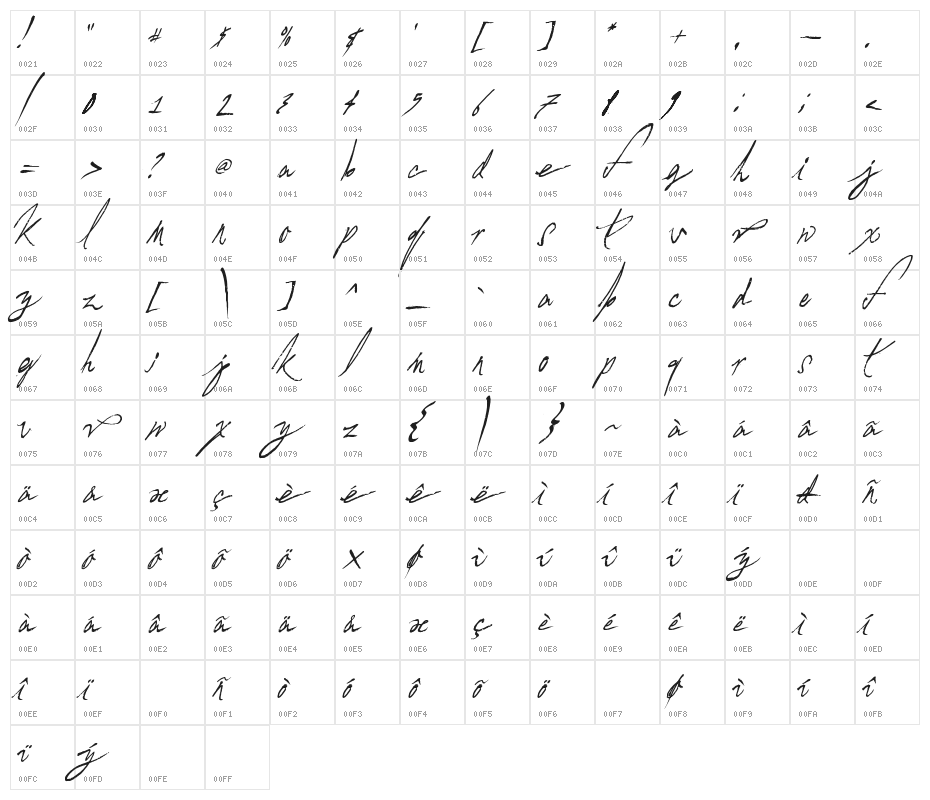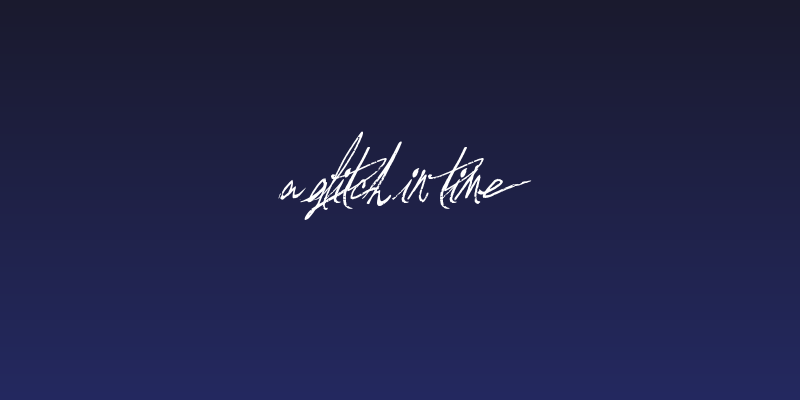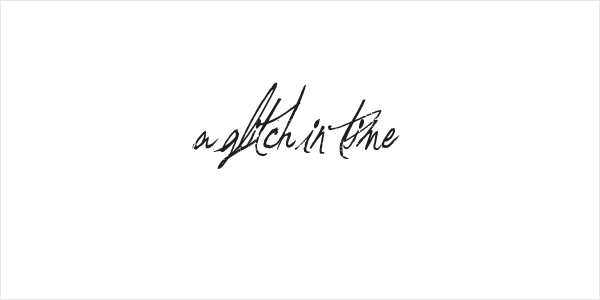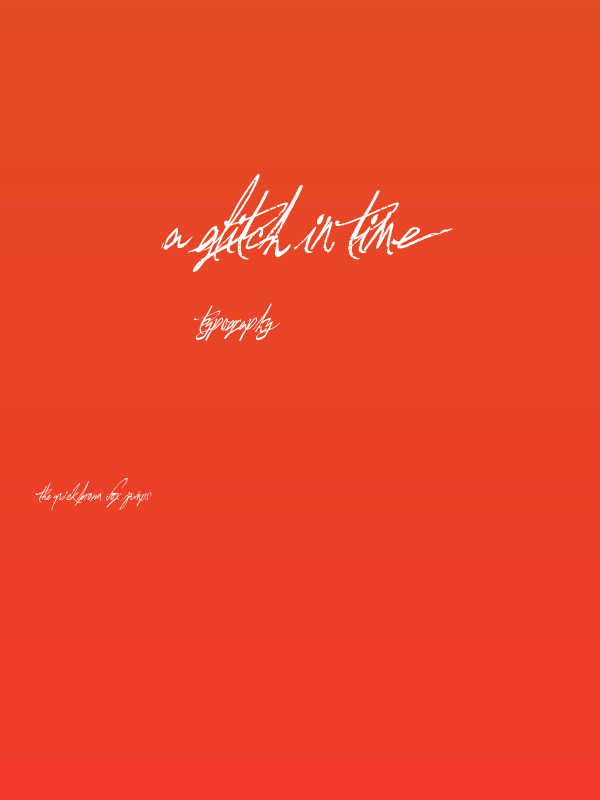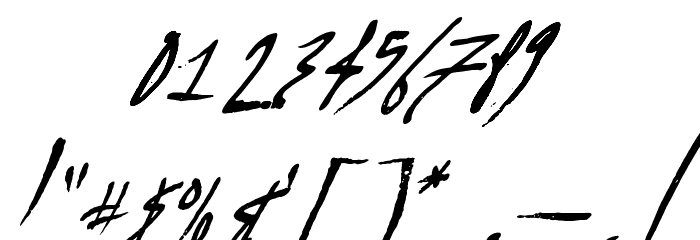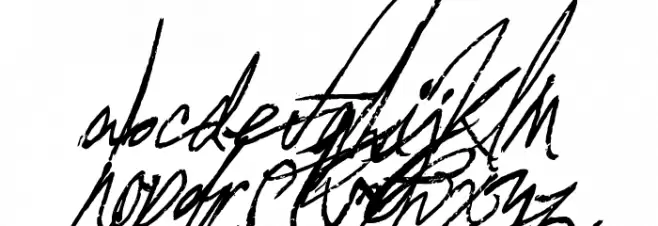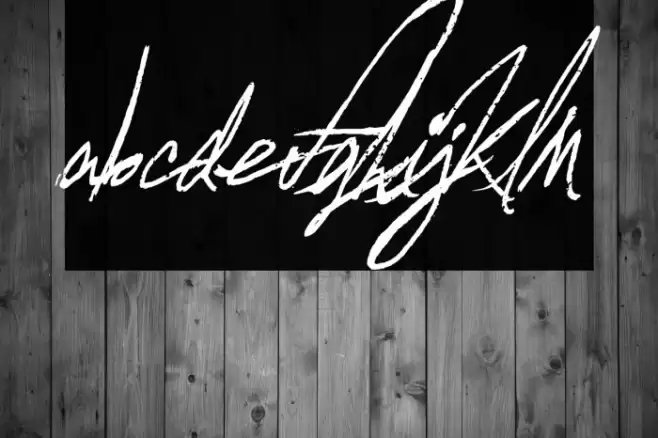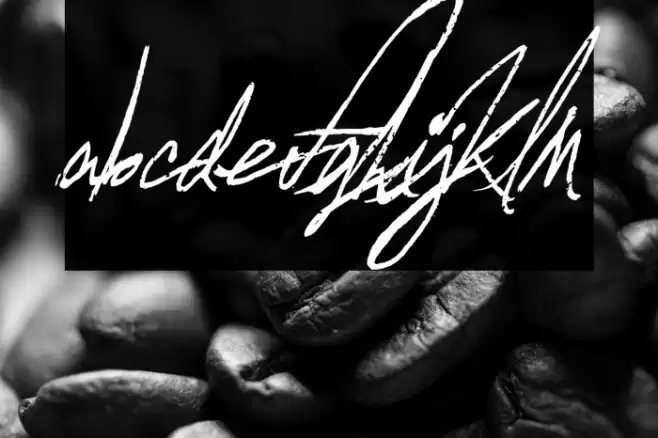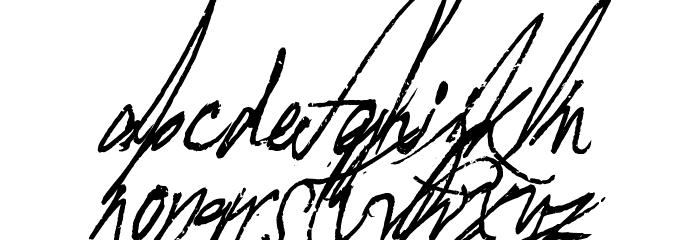
A Glitch In Time Font
| 用途 | Logos, Headlines, Artistic designs |
| おすすめプロジェクト | Ideal for artistic projects, album covers, posters, and any design needing a bold, unconventional touch. |